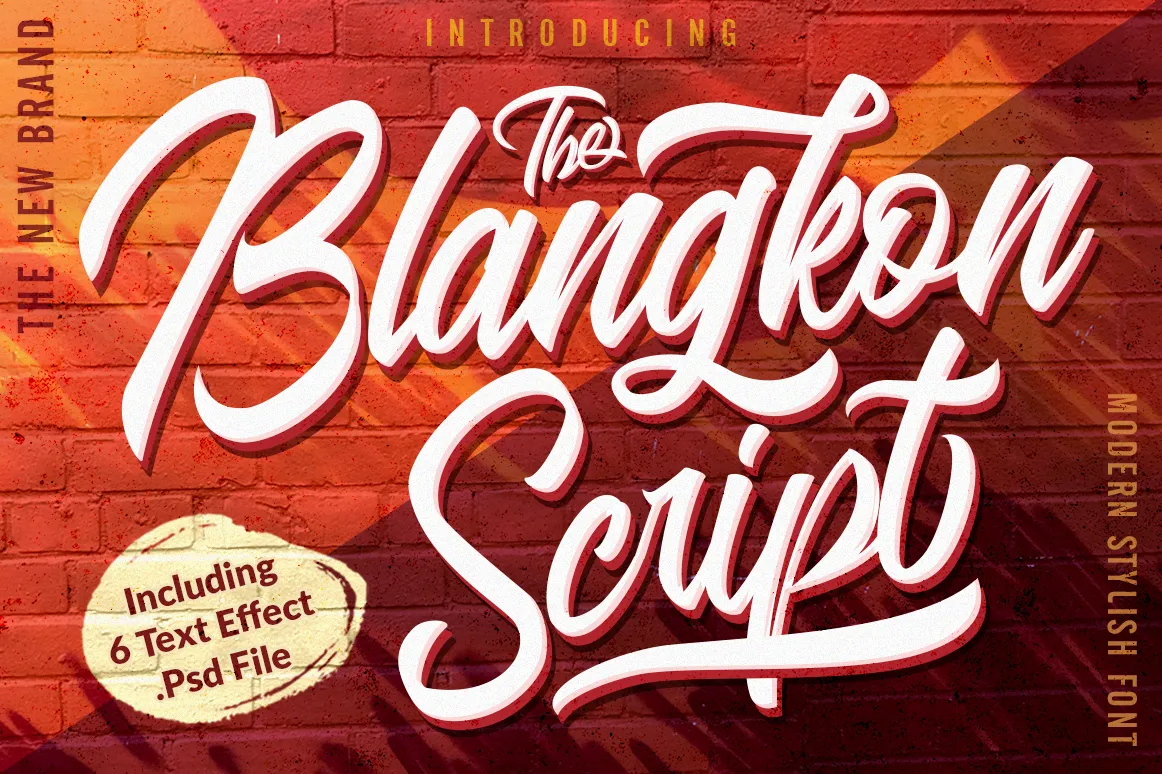
Blangkon Script Font – Download Grátis
A Blangkon Font é uma tipografia script criada pelo Kotak Kuning Studio inspirada na arte do streetwear contemporânea. Com seu toque naturalmente autoral, ela adiciona um toque pessoal a qualquer projeto de design, tornando-o único e original. Este font oferece perfeita aplicação para diversas áreas, como logomarcas e marcas, convites, cartões de papelão, designs de casamentos, publicações nas redes sociais, anúncios e embalagens de produtos. Suas linhas elegantes e harmoniosas combinam bem com diferentes estilos de design e torna-a uma excelente escolha para qualquer necessidade gráfica.